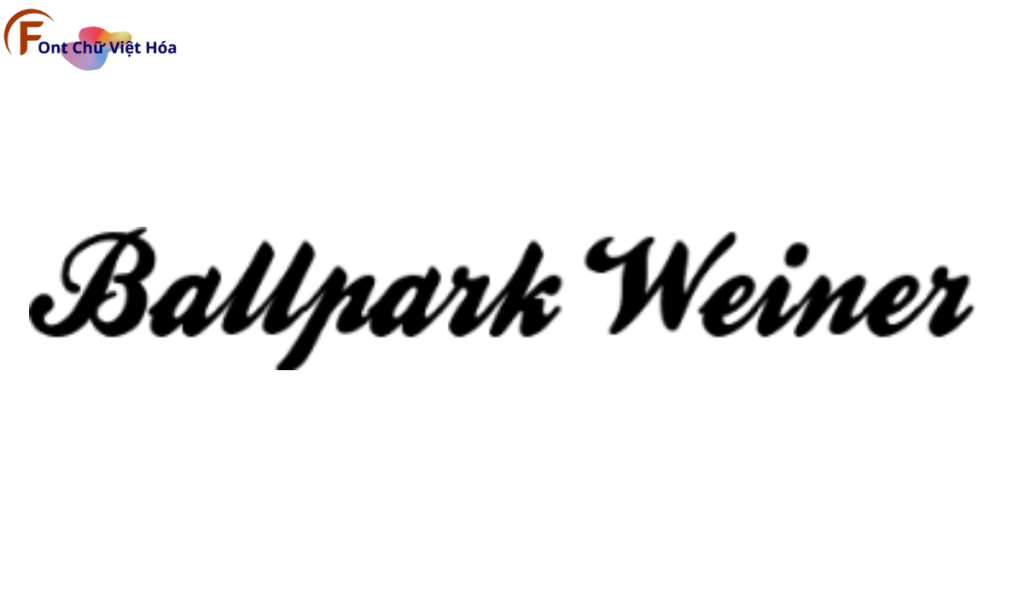
Ballpark Weiner Font SVN Việt Hóa
Ballpark Weiner Font SVN Việt Hóa là một font chữ viết tay cá tính, thuộc bộ font SVN. Được thiết kế với mục tiêu mang lại sự mềm mại và thanh thoát, font này lý tưởng cho các dự án thiết kế như thiệp mời, logo, và bao bì sản phẩm. Với các nét chữ uyển chuyển và độ dày đều đặn, Ballpark Weiner Font SVN Việt Hóa không chỉ dễ đọc mà còn tạo cảm giác thân thiện và gần gũi. Việc Việt hóa font giúp người dùng dễ dàng sử dụng trong các thiết kế tiếng Việt, mang lại sự tiện lợi và thẩm mỹ cao.